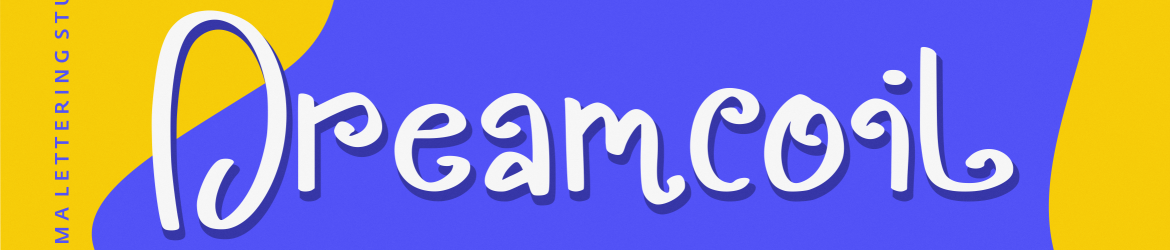
A Dreamcoil Font é uma elegante caligrafia detalhada e com curvas suaves perfeita para quem busca uma mistura de sofisticação e alegria nos seus designs. Esta fonte é definida por suas linhas fluidas e elegantes, criando um visual chamativo que se destaca em qualquer design. A Dreamcoil Font é ideal para usar em marca de moda ou design editorial, trazendo um toque moderno e sofisticado aos projetos. Com a sua caligrafia detalhada e curvas perfeitamente definidas, você pode confiar nas suas capacidades e deixar que essa fonte transforme qualquer projeto com uma graça única. Adicione-a à sua próxima ideia de design, e certamente você vai amar o resultado final.